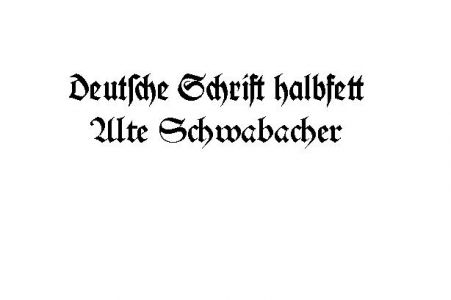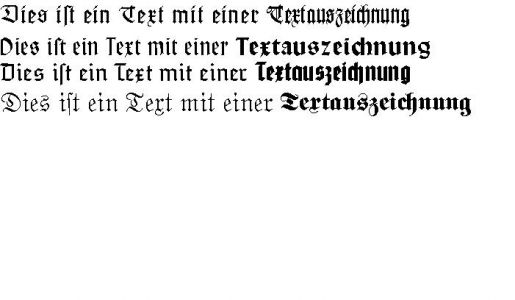
Journal-Kursiv von 1913 und Solidaritäts-Adresse
heute habe ich eine sehr seltene Fraktur-Variante gedruckt: Eine Journal-Kursiv der Ludwig Wagner A.-G., Leipzig, nach einem Entwurf von Rudolf Engelhardt, die ich Euch hier zeigen möchte. Nur so, weil sie so schön ist. Und weil kursive Fraktur-Versionen sehr selten waren in dieser Zeit. Auf Anhieb fällt mir noch die Weiß-Fraktur kursiv ein von 1909.
Journal-Kursiv:
Auf Anhieb fällt mir da noch die „Deutsche Kursiv“ von Richard Ludwig
Ludwig & Mayer, Frankfurt am Main, 1909 ein.
>echte Kursive
Sind echte Italic-Schnitte nicht (allein) Antiquas vorbehalten?
Auszeichnungen in Fraktur setzen, war doch seinerzeit das Sperren von Text bzw. einen fetten Schnitt benutzen.
Was die kursive Fraktur angeht, im Studium ist mir im Kalligrafieunterricht mal eine wunderschöne Kupferstecherfraktur begegnet von Mathias Merian, glaub ich. Wenn Du mal sowas im Musterbuch hast, würd ich mich freuen es zu sehen. Aber wahrscheinlich gibt es die als Druckschrift nicht.
>…oder ein Paar Worter in der Schwabacher zu setzen, wenn der Text sonst in einer Fraktur war.
3) Walbaum Fraktur und Schwabacher - ich finde das passt nicht zusammen...
Genau deswegen haben Leute sie so verwendet!
Klar, ist eine fettere Schnitt die bessere Auswahl, zumindest in meiner Augen. Aber Schriftsetzer haben früher so gearbeitet. Fettere Versionen von Textschnitte ist etwas, dass erst während des 19. Jahrhunderts in der Entwicklung kam, denke ich (siehe Antiqua- und Grotesksatz). Aber die Kunst, die Fraktur zu setzen, geht auf die 16. Jahrhundert zurück.
Nein. Ich habe diese Mischung in alte Schriftmusterblätter gesehen (ca. 17. bis 19. Jahrhundert). Die Mischung habe ich auch auf Titelseiten von uralte Bücher gesehen. Leider habe ich keine Fotos in meiner Sammulung davon :oops:
Von Albert Kaprs "Fraktur: Form und Geschichte der gebrochenen Schriften", Seite 214:
Bei Fraktur als Grundschrift hat die Schriftmischung eine lange Tradition: Man verwendet für die hervorzuhebenden Passagen eine Schwabacher, die durch ihren anderen Duktus und ihre andere Fette auszeichnet. Auch möglich, aber eher in Überschriften als im Text, ist eine gotische Schrift als Auszeichnung.
Danach folget ein Beispeil, aber ich habe weder Kamera noch Scanner momentan bei mir.
Mit Sicherheit muss mann eine PASSENDE Schwabacher auswählen. Nur weil die Walbaum Fraktur und eine "spezifische Schwacher Schrift in digitalen Form" nicht gut aussieht, heißt nicht, dass dies keine Möglichkeit ist.
Leider unter alle die gebrochene Schriftarten ist es die Schwabacher, von denen es am wenigsten gute digitale Fonts gibt.
Natürlich gibt es unterschiedliche Fraktur- bzw. Schwabacher und unter diesen befinden sich bestimmt manche die besser miteinander korrospondieren... Aber als "ungläubiger Thomas" glaube ich erst etwas, wenn ich es sehe :D
Falls jemand Bildmaterial zur Mischung Fraktur/Schwabacher hat, bitte posten.
Das ergibt in der Regel ein durchaus homogenes Satzbild und kann sehr übersichtlich sein. Größere Auswahl schließt ja (die für Dich so wichtige) Ordnung und Normierung nicht aus: Gerade bei komplizierten – wissenschaftlichen – Werken ist die größere Auswahl der Auszeichnungen recht nützlich. – Dass man einfach Schriften wild mischte, weil es vermeintlich ‹schön› aussah, das begann erst so richtig im 19. Jahrhundert.